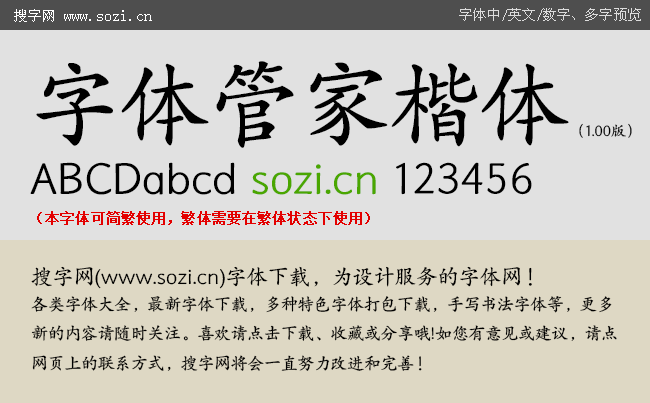
字體管家楷體
搜字網(wǎng)提供字體管家楷體中文字體下載,字體管家楷體是一款應(yīng)用于設(shè)計(jì)方面的中文簡體漢字,該字體字體端正簡潔,整體效果十分出色,可以應(yīng)用于廣告設(shè)計(jì)、名片設(shè)計(jì)、包裝印刷、產(chǎn)品設(shè)計(jì)等應(yīng)用。